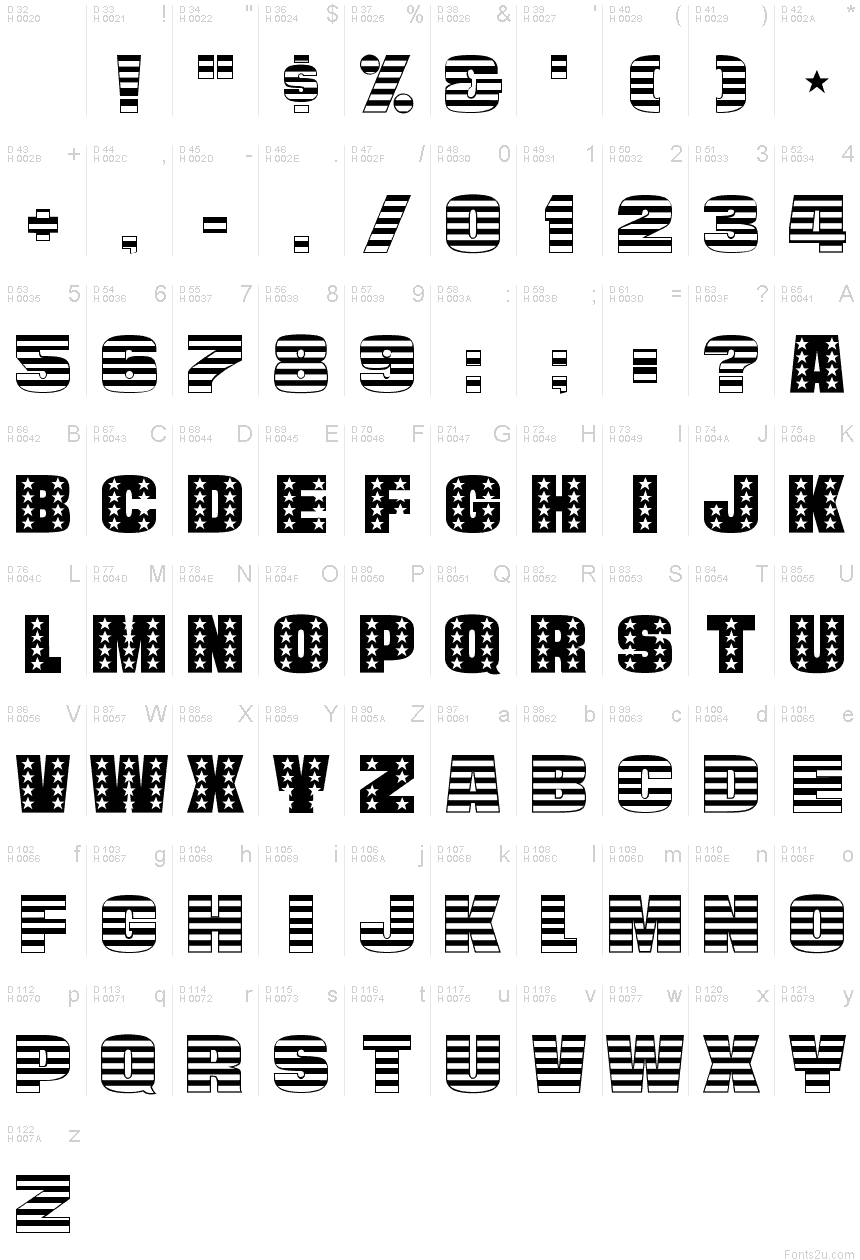
Stars And Stripes Plain, autorstwa Pata Snydera, to darmowy, patriotyczny krój pisma typu display, utrzymany w stylistyce amerykańskiej flagi. Litery są duże, blokowe i mają wyrazisty charakter: poziome pasy przebiegają przez znaki, a grupy gwiazd pojawiają się w miejscu, w którym na fladze znajduje się kanton. Dzięki temu krój zyskuje śmiały wygląd rodem z festiwalowych transparentów, zamiast sprawiać wrażenie jedynie neutralnego elementu ozdobnego.
Idealnie sprawdzi się na plakatach na 4 lipca, ulotkach wyborczych, banerach imprezowych, pamiątkowych koszulkach oraz szyldach sklepowych, gdzie liternictwo samo w sobie tworzy klimat. Jako darmowy font świetnie nadaje się również do nagłówków na okładkach, plansz tytułowych i krótkich haseł – wzór flagi prezentuje się najlepiej, gdy słowa są krótkie, a wielkie litery mają przestrzeń, by go wyeksponować.